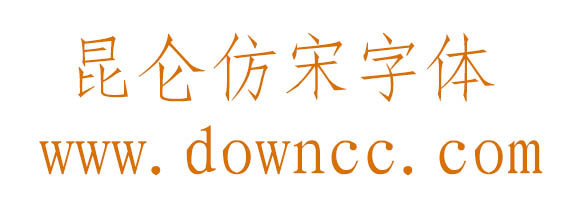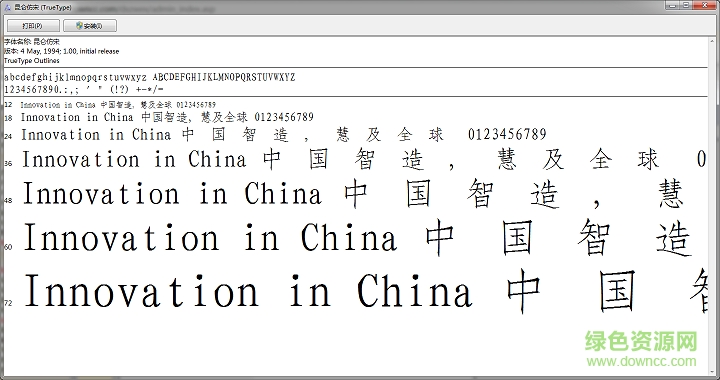
昆侖仿宋是一款帶有勾腳的中文簡(jiǎn)體字。因?yàn)槊總€(gè)豎筆畫的部分都會(huì)突出一點(diǎn),像帶有勾腳樣,整體字形還是很細(xì)膩的。趕快到綠色資源網(wǎng)下載體驗(yàn)吧!
昆侖仿宋是我們生活中使用較多的字體, 字體的線條整體來說比較細(xì),辨識(shí)度高